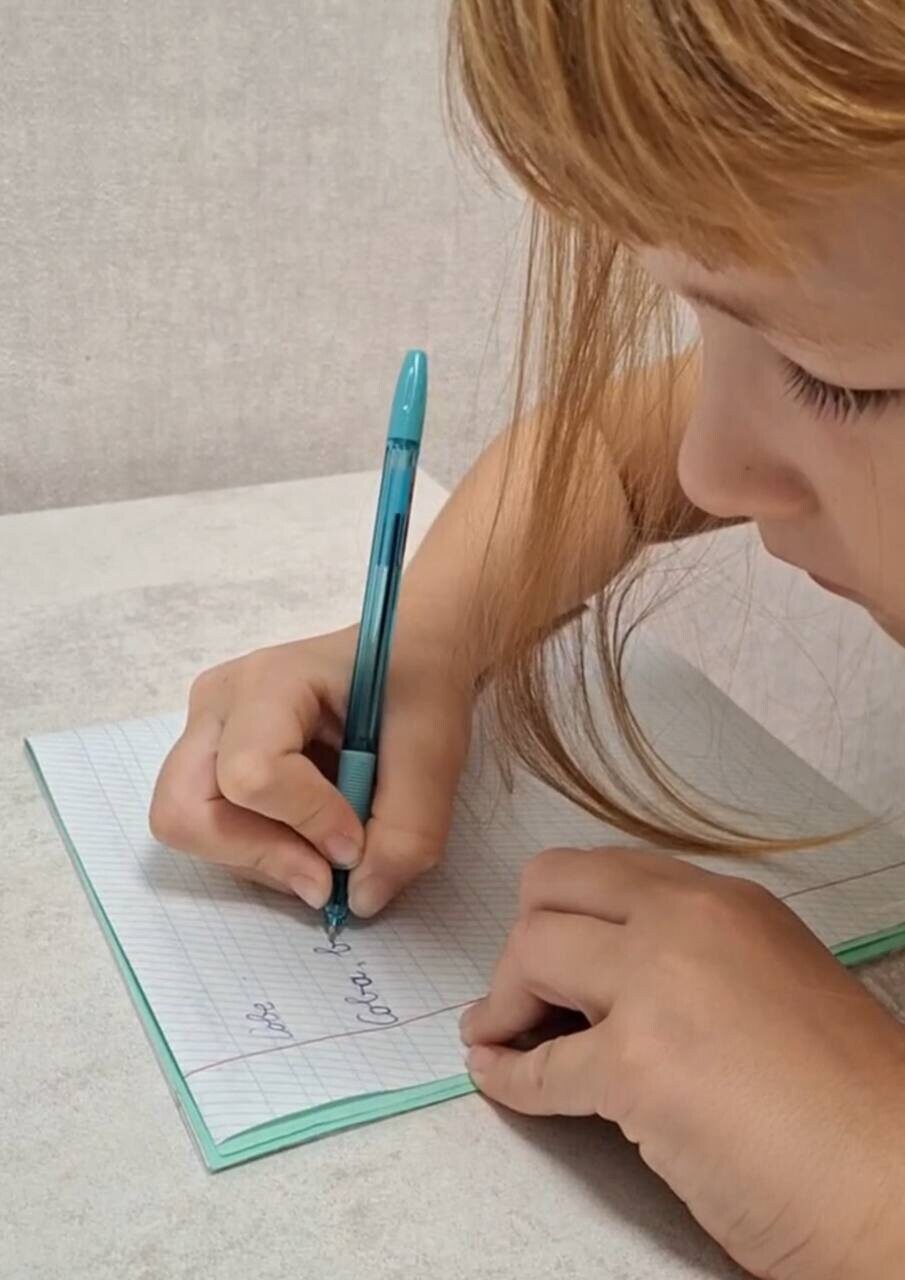
Часто, разглядывая тетрадь ребенка, мы видим общую «грязь», неразборчивость и хаос. Нам кажется, что нужно исправлять всё сразу: и наклон, и размер букв, и аккуратность. Но как эксперт, я хочу поделиться с вами удивительным открытием, которое мы сделали за десять лет исследований и практики в онлайн-школе каллиграфии KidsLetters: в основе большинства проблем с письмом лежит один-единственный элемент — овал.
Овал — это не просто «кружочек». Это своего рода «магический ключ», который открывает дверь к понятному и быстрому письму. Если этот элемент освоен неправильно, всё здание навыка начинает рушиться, превращая учебу в тяжкое испытание. Давайте разберемся, почему один маленький овал обладает такой огромной властью над всем процессом обучения.
Буква как след движения: техника «спорта» на бумаге
Главное, что нам нужно осознать: письмо — это не рисование статичных картинок, это движение. А каждая буква — лишь след этого движения. Представьте себе профессионального пловца или стрелка из лука. Их успех зависит не от силы мышц, а от выверенной техники. Если пловец неправильно делает гребок, он быстро устанет и не придет к финишу первым.
Точно так же и в письме. Существует строгое правило: все овалы в русском языке пишутся против часовой стрелки. Это закон механики письма. Но сегодня мы видим пугающую картину: дети массово пишут овал по часовой стрелке, «как получилось» или «как увидел».
Когда направление движения нарушено, письмо «ломается». Оно перестает быть потоковым и легким. Ребенку приходится каждый раз прикладывать титанические усилия, чтобы соединить буквы между собой. Это всё равно что пытаться бежать, завязывая шнурки на ходу. Если техника (вектор движения) неверная, письмо никогда не будет быстрым и красивым, сколько бы ребенок ни «старался».
Правило 60%: один элемент — семнадцать букв
Почему я называю овал «магическим»? Потому что он является фундаментом для огромного количества букв. Вдумайтесь в эту цифру: овал — это основа для 60% всего алфавита. Семнадцать букв строятся на базе этого элемента. Буквы «О», «А», «Д», «Б», «Ю», «Ц» — все они содержат в себе овал или его производные.
Если ребенок не понимает логику овала, он автоматически делает ошибки в половине алфавита. Но стоит только «починить» этот один элемент, как по цепочке выравниваются все остальные буквы. Это тот самый «больной зуб», который нужно вылечить в первую очередь. Пока он болит (пока овал пишется неправильно), нет смысла заниматься «косметикой» — выравнивать наклон или высоту. Исправив овал, вы решаете более половины проблем с почерком одним точным действием
Ловушка «33 вариаций» и педагогическая запущенность
В современной школе на обучение письму отводится всего 12 недель. Это катастрофически мало. В результате мы сталкиваемся с тем, что я называю «педагогической запущенностью»: ребенку просто не успевают объяснить алгоритм. Ему говорят: «пиши аккуратно», но не показывают, как это движение рождается.
Для мозга ребенка, который не понимает логики овала, каждая из 33 букв — это отдельная, сложная задача. Он каждый раз заново выдумывает, где начать, куда вести и как закончить. Это создает колоссальную когнитивную нагрузку. Но когда мы показываем ему, что 17 букв — это один и тот же овал, мозг расслабляется. Вместо тридцати трех операций ему нужно запомнить одну.
Когда нет четкой системы и правил соединения (например, когда ребенок не знает, что «Л» или «М» требуют своей «ножки» и правильного примыкания к овалу), буквы начинают превращаться в неразборчивые каракули. Мы видели примеры тетрадей даже девятиклассников, которые пишут слово «слышно» как «ышно», потому что у них просто «исчезли» соединения и части букв из-за неверной траектории овала. Это не лень — это отсутствие автоматизированного правильного движения.
Чтобы ваш ребенок перестал «изобретать велосипед» над каждой строчкой и почувствовал радость от того, что рука его наконец-то слушается, важно дать ему эту простую и ясную технику.
От хаоса к автоматизму: почему это важно сейчас
Мы живем в цифровом мире, где письмо кажется второстепенным. Но именно письмо — это фундамент развитой речи и мышления. Если ребенок тратит все свои силы на то, чтобы вспомнить, как пишется буква, у него не остается ресурса на орфографию, на смысл текста, на творчество. Его «батарейка» садится уже на первой строчке.
Исправление овала дает ребенку ощущение победы. Когда он видит, что буквы «А» и «О» вдруг стали ровными, а рука перестала болеть, у него появляется та самая мотивация «Я могу», о которой мы все мечтаем. Письмо становится естественным, как дыхание.
Дорогие родители, не требуйте от ребенка невозможного «старания», если у него нарушена техника. Помогите ему увидеть логику в этом конструкторе из букв. Начните с овала — и вы увидите, как зажатость сменится легкостью, а грязная тетрадь — аккуратными строчками, за которыми стоит уверенный в себе и спокойный ученик. Ведь когда мы знаем, куда вести руку, нам больше не нужно бояться бумаг